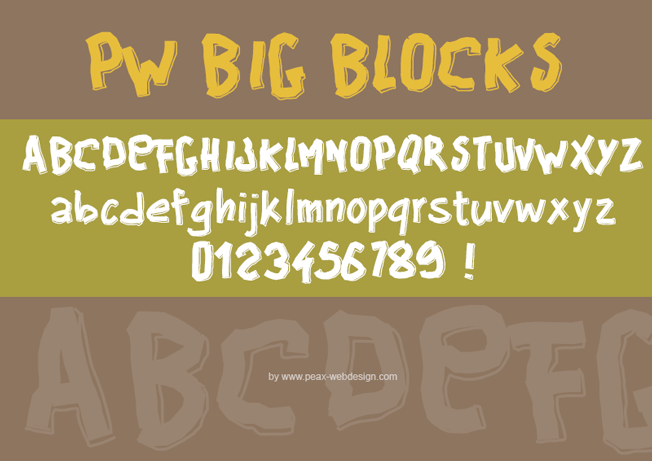
PW Big Blocks, police manuscrite cartoon.
PW Big Blocks est une typo un peu sinueuse, déséquilibrée, un peu cartoon aussi : elle est très appropriée pour les gros titres, bien que les minuscules existent également. La hauteur et l'inclinaison des différentes lettres sont volontairement disparates, ce qui crée le charme de cette police.